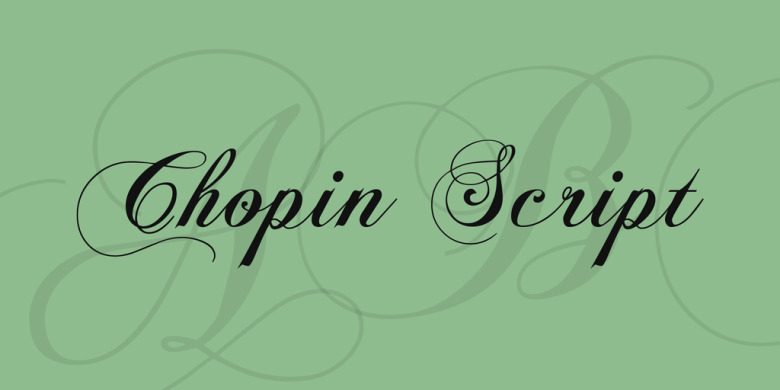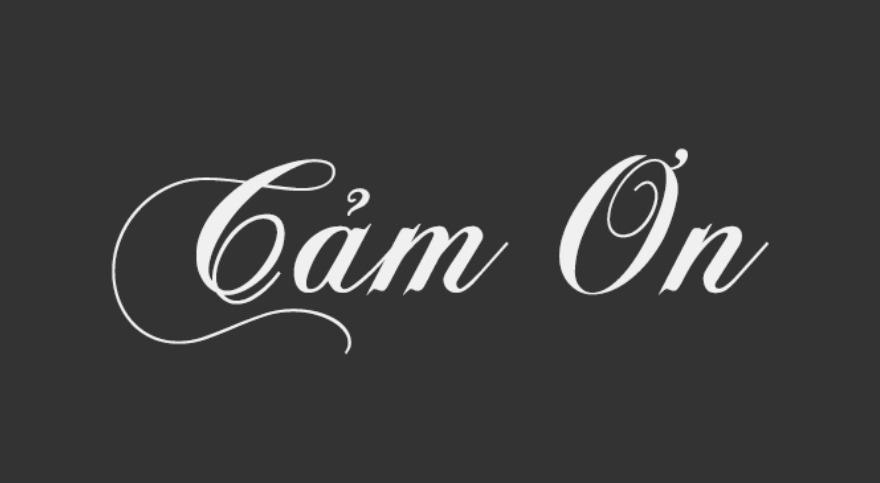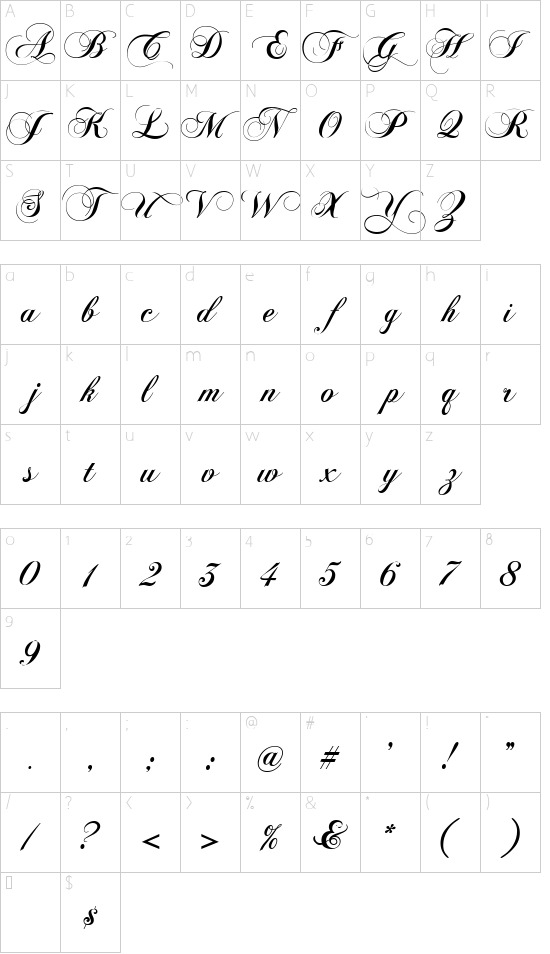
Font UVF Chopin Script là bộ phông chữ thư pháp phương Tây kinh điển, mô phỏng sinh động những đường nét bút sắt thanh mảnh đầy chất thơ của thế kỷ 18. Lấy cảm hứng từ những bản nhạc giao hưởng lãng mạn, kiểu chữ này mang lại vẻ ngoài quý phái, thanh tao cho các bản vẽ phối cảnh homestay phong cách cổ điển, thiệp mời sự kiện hay biển tên khu nghỉ dưỡng.
Nét đẹp vũ khúc cổ điển của font UVF Chopin Script trong thiết kế
Điểm lôi cuốn đặc trưng của font UVF Chopin Script nằm ở nhịp điệu chuyển động uyển chuyển giữa các nét thanh siêu mảnh và các nét nhấn đậm đà, mô phỏng động tác đưa bút mực linh hoạt của các nghệ nhân viết chữ xưa. Những đường cong uốn lượn rộng rãi tạo cảm giác thoáng đãng, mang đến chiều sâu nghệ thuật và sự trang nhã cho bất kỳ mặt bằng thiết kế nào.
Khả năng biểu đạt cảm xúc của phông chữ này cực kỳ thích hợp cho các dự án đòi hỏi tính thẩm mỹ truyền thống hoặc phong cách kiến trúc bán cổ điển. Thay vì sự thô cứng của các khối chữ in hiện đại, Chopin Script mang lại cảm giác ấm cúng, tinh tế và sự tôn trọng các giá trị thủ công. Đây là phương án phù hợp để định hình phong cách cho các không gian nghỉ dưỡng boutique, nhà vườn sinh thái hoặc những thương hiệu muốn nhấn mạnh vào tính cá nhân hóa và gu thẩm mỹ thanh lịch.
| Phân loại phong cách | Calligraphy / Formal Script / Classic |
| Mục đích phù hợp | Biển tên villa, thiệp sự kiện, tiêu đề phối cảnh |
Tư vấn từ chuyên viên: UVF Chopin Script có độ trang trí và tương phản nét rất cao. Để bố cục bản thiết kế đạt hiệu quả thị giác tốt, bạn chỉ nên sử dụng phông chữ này cho các tiêu đề chính hoặc lời tựa ngắn. Đối với các nội dung thuyết minh kỹ thuật chi tiết, hãy phối hợp cùng một phông có chân truyền thống như Times New Roman hoặc phông không chân tối giản để người đọc dễ tiếp nhận thông tin.
03 Ứng dụng phông chữ Chopin Script vào không gian thực tế
Nhờ vẻ ngoài giàu chất nghệ thuật và tính hoài niệm, bộ phông chữ này mang lại giá trị cao trong khâu trang trí và quảng bá các công trình hiện đại:
- Hệ thống biển hiệu cho khu nghỉ dưỡng và Villa: Những đường nét bay bổng của Chopin Script rất ăn ý khi gia công trên chất liệu đồng thau, inox mạ vàng gương hoặc gỗ tự nhiên. Phông chữ này giúp các căn homestay lắp ghép toát lên vẻ quý phái và tạo ấn tượng khó phai với du khách.
- Trang trí không gian tiệc cưới và sự kiện: Bạn có thể sử dụng phông chữ này để thiết kế backdrop, biển chào hoặc bảng tên khu vực tại các sảnh tiệc trong khuôn viên nhà lắp ghép, tạo nên bầu không khí lãng mạn và trang trọng.
- Thiết kế bìa hồ sơ năng lực kiến trúc: Sử dụng font UVF Chopin Script cho các dòng tựa đề hay tên dự án giúp hồ sơ của bạn trông chỉn chu như một tác phẩm mỹ thuật, thể hiện sự tinh tế và tâm huyết của đơn vị kiến tạo.
03 Lưu ý để khai thác phông chữ UVF Chopin Script không bị rối mắt
Để khai thác hiệu quả vẻ đẹp của dòng font thư pháp cổ điển này mà không làm giảm tính thẩm mỹ của bản thiết kế, người thiết kế nên lưu tâm một số kinh nghiệm sau:
- Không viết hoa toàn bộ từ ngữ: Các chữ hoa của Chopin Script có độ uốn lượn rất phức tạp. Việc viết hoa liên tiếp nhiều ký tự sẽ làm các nét móc đè lên nhau, gây mất trật tự thị giác và khiến câu văn trở nên khó đọc.
- Cân đối khoảng cách dòng: Do các nét vươn lên trên và kéo xuống dưới của phông chữ rất dài, bạn cần nới rộng khoảng cách giữa các dòng văn bản để các ký tự không bị va chạm vào nhau.
- Lựa chọn kích thước hiển thị vừa đủ: Do có những nét thanh cực kỳ mảnh, bạn không nên sử dụng phông chữ này ở kích thước quá nhỏ, vì các nét mảnh có thể bị đứt đoạn khi in ấn trên các chất liệu nhám hoặc bạt quảng cáo.